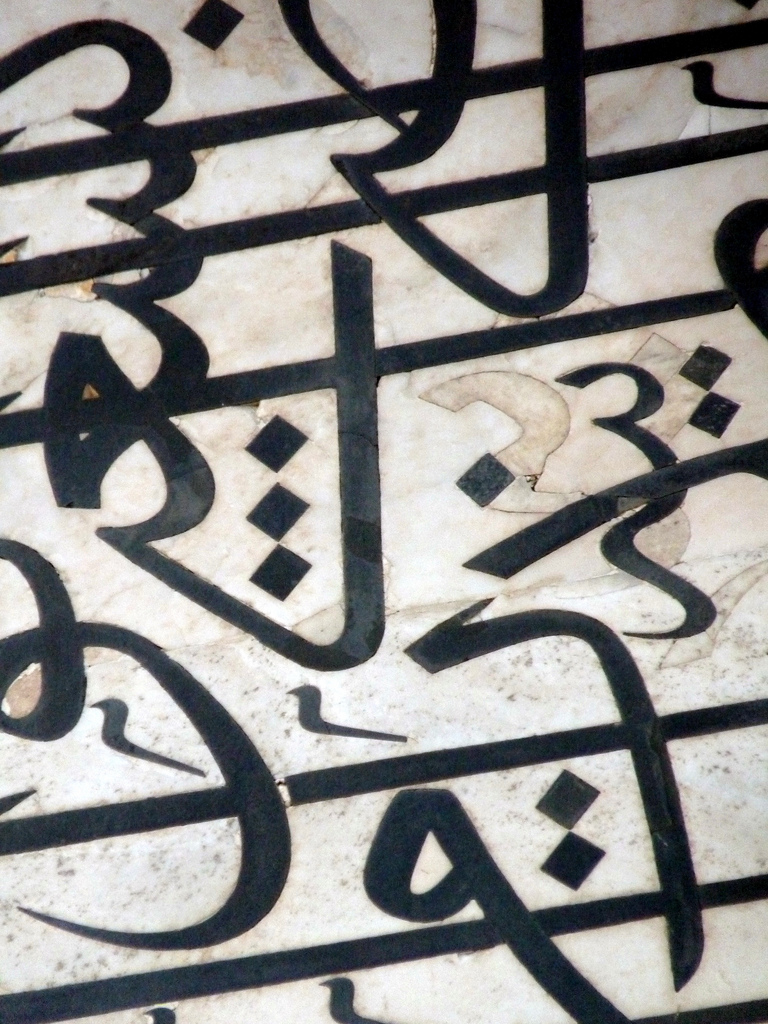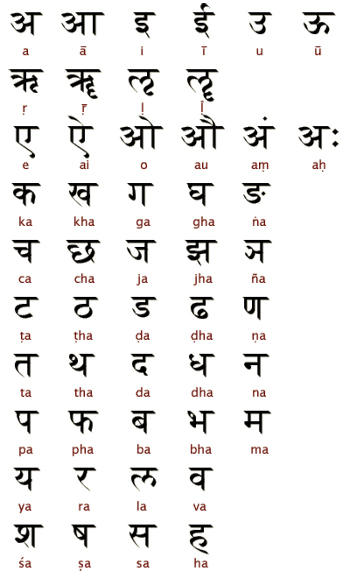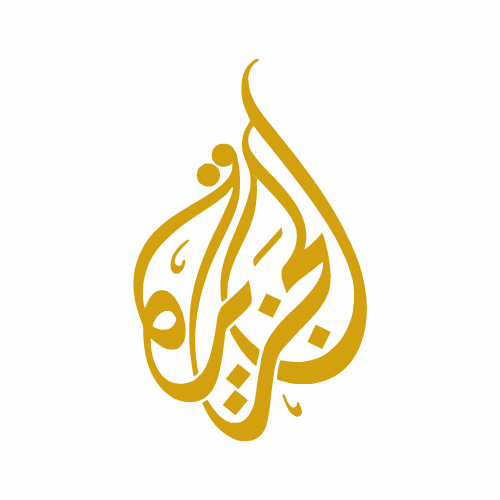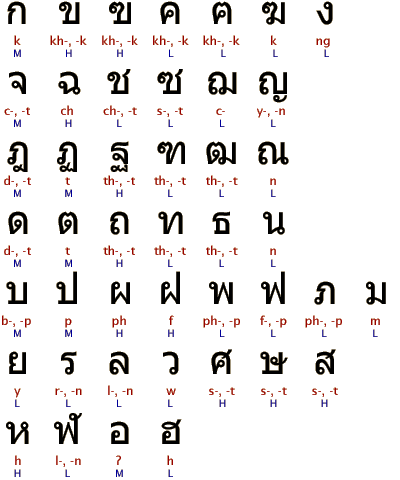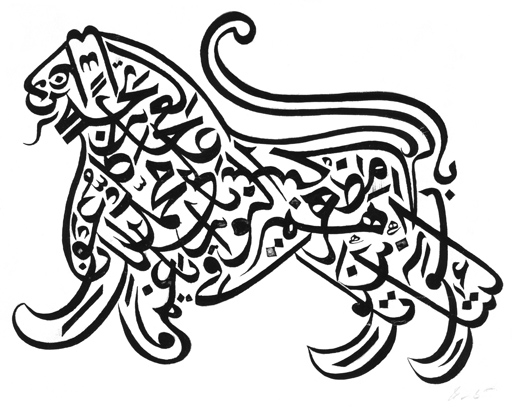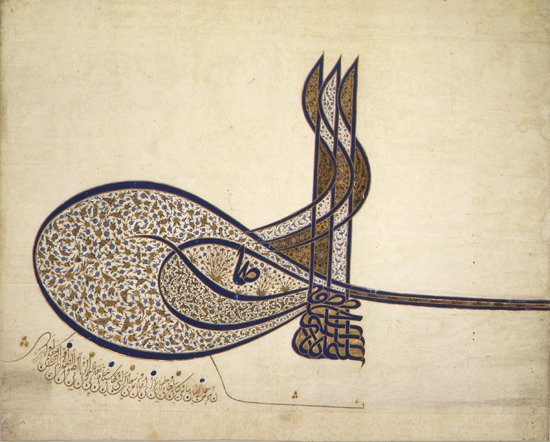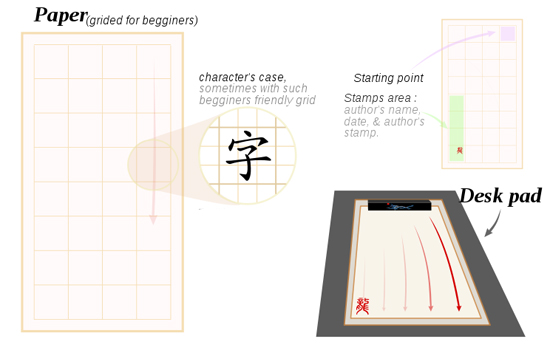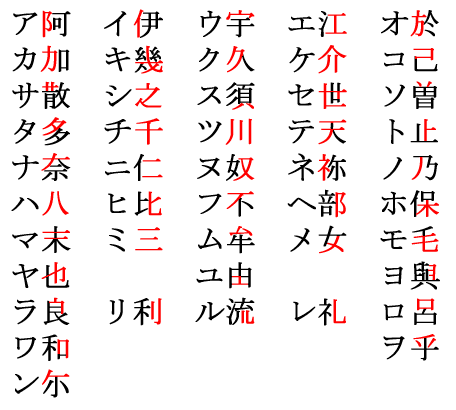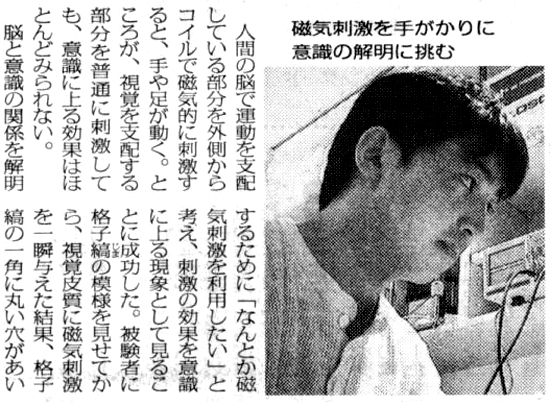
La Belleza de la tipografía: Sistemas de escritura y Caligrafía de alrededor del mundo
La belleza de la tipografía no conoce fronteras. Mientras la mayoría de nosotros trabaja con el familiar alfabeto latino, proyectos internacionales generalmente necesitan un gran conocimiento de sistemas de escrituras menos conocidos de alrededor del mundo. La estética y estructura de este tipo de diseño puede estar fuertemente ligada a la forma y legibilidad de las formas de las letras, así que aprender sobre sistemas de escritura internacionales te ayudara a crear diseños mas llamativos y atractivos.
Escoge cualquier lenguaje que quieras, como: Arabe, chino, japonés,o ¿tal vez nepalés? cada uno esta basado en un sistema de escritura diferente, lo cual hace interesante el comprender como funcionan. Hoy, cubriremos cinco categorías de sistemas de escritura. Sonara tedioso y académico, pero no lo es. Si uno se toma el tiempo para entenderlos, descubre que todos tienen algo especial que aportar. Hemos tratado de presentar al menos una característica especial de cada lenguaje de la cual puedan tomar algo de inspiración y aplicarla a su propio trabajo de tipografía. Cubriremos: Sistemas de escritura de Extremo Oriente, escritura Arábiga e Hindú ( Brahámico).Si hay interés, hablaremos sobre cirílico, hebreo y otros sistemas de escritura en otro post.
Sistemas de escritura de Extremo Oriente
Obviamente, el chino usa caracteres chinos ( donde son conocidos como hanzi). Pero los caracteres chinos también son usados de diferentes maneras en el japonés ( donde son conocidos cono kanji) y el coreano ( hanja). En esta sección, veremos a los cuatro sistemas de escritura de extremo oriente: Chino, japonés, coreano y vietnamita.
Caracteres chinos
Los caracteres chinos son símbolos que no comprenden un alfabeto. Este sistema de escritura, en el cual cada carácter  generalmente representa ya sea una palabra de una sílaba o una sílaba que forma parte de una palabra, se conoce como logo-silábico. Esto también significa que cada carácter tiene su propia pronunciación, y no hay manera de adivinarlo.Sumado a esto esta el hecho de que para saber leer y escribir el chino más básico necesitas memorizar mas de 4000 caracteres. Afortunadamente para nosotros, no necesitamos aprender chino para apreciar la belleza de su escritura.
Porque muchos de los caracteres chinos mas usados tienen de 10 a 30 trazos, cierto orden en su trazo se recomienda para asegurar la velocidad, precisión y legibilidad en la composición. Así que cuando uno este aprendiendo un nuevo carácter tiene que aprender el orden en el que se escribe, y la secuencia tiene ciertas reglas generales, como: de arriba hacia abajo, de izquierda a derecha, lo horizontal antes que lo vertical, lo de en medio antes que a los lados, caer a la izquierda antes que a la derecha, el exterior antes que el interior, el interior antes de cerrar los trazos.
Los ocho principios de Yong
Los trazos en el chino se dividen en ocho categorías principales: horizontales (一), verticales (丨), caen a la izquierda (丿), caen a la derecha (丶), ascendentes,puntos (、), ganchos (亅) y doblados (乛, 乚, 乙, etc.). Los ocho principios de Yong muestran como escribir estos trazos, que son comunes en caracteres chinos y pueden encontrarse todos en el carácter “yǒng” (永,que se traduce como » eternidad o «permanencia). se creía que practicar estos principios frecuentemente como un calígrafo principiante aseguraría belleza en la escritura.
Los cuatro tesoros del Estudio
“Los cuatro tesoros del estudio” es una expresión que se refiere a el pincel, la tinta, el papel,y la piedra para tinta que se usan en las tradiciones caligráficas chinas y de otras partes de extremo oriente. La cabeza del pincel puede estar hecha de cabello ( o plumas) de una variedad de animales, incluyendo, lobos, conejos, venados, gallinas, patos, cabras, cerdos y tigres. Los chinos y japoneses también tienen la tradición de hacer pinceles con cabellos de recién nacidos, como un regalo único en la vida para el niño.
Sellos y pasta
El artista por lo regular termina sus trabajos de caligrafía agregando su sello al final con tinta roja. El sello sirve como firma y generalmente esta hecho en un estilo antiguo.
Escritura vertical y horizontal
Muchas escrituras del extremo oriente ( como la china, japonesa y coreana) pueden ser escritas de manera horizontal y vertical, porque consisten principalmente de unidades silábicas desconectadas, cada una de las letras comprende un marco cuadrado imaginario. Tradicionalmente, el chino se escribe en columnas verticales, de arriba hacia abajo, la primer columna en la parte derecha de la página, y el texto empieza a la izquierda.
En tiempos modernos, el uso de la disposición de página occidental de filas horizontales que van de derecha a izquierda y que se leen de arriba hacia abajo se ha vuelto más popular. Señalizaciones son particularmente difíciles para ser escritas en chino pues pueden ser escritas tanto de derecha a izquierda y viceversa ( este último siendo parte de la composición tradicional, con cada columna siendo un carácter de ancho) y también de arriba hacia abajo.
Diferentes estilos
En la caligrafía china, las letras pueden ser escritas en 5 estilos principales. Estos estilos son intrinsecos a la historia de la escritura china.
La Escritura de sellos es el estilo más antiguo y continua siendo ampliamente practicado, aunque mucha gente ahora ya no puede leerlo. Es considerada una escritura antigua, generalmente no se usa más alla de la caligrafía o sellos tallados, de ahí su nombre.